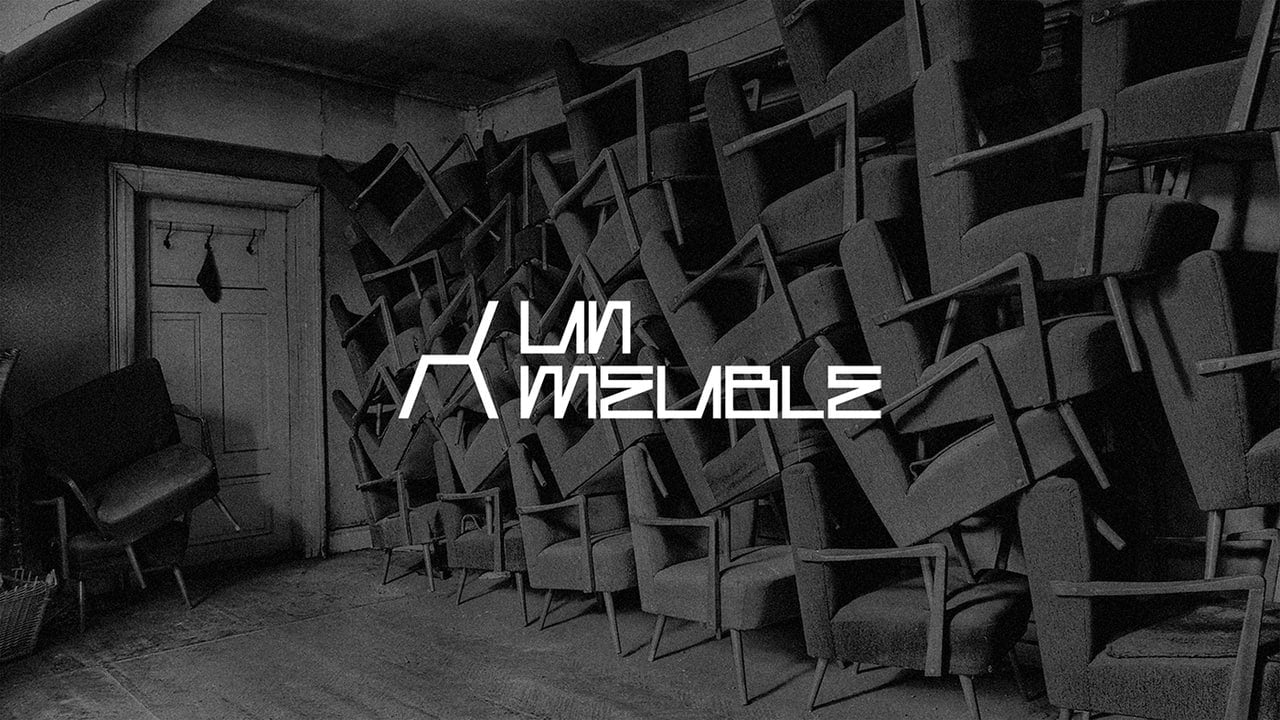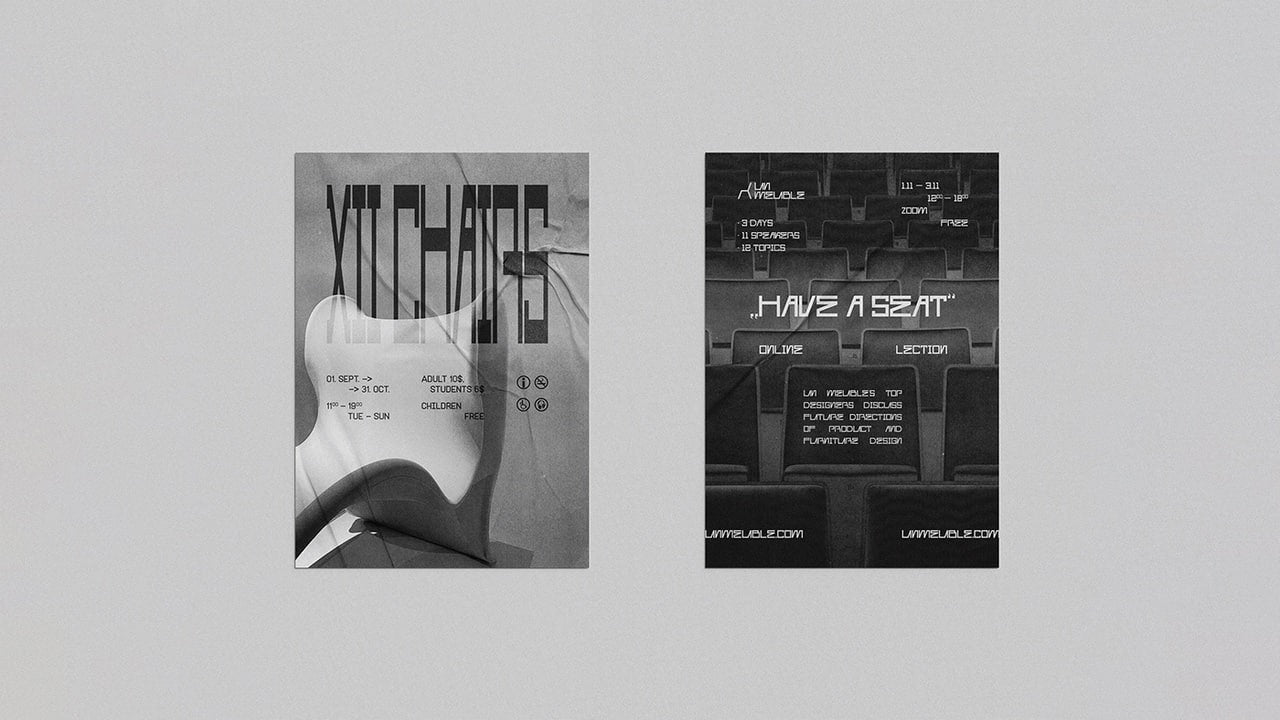
Un Meuble Display Font
Inspirée par le design épuré d'un logo créé pour un magasin de meubles conceptuel par Iryna Kovalenko, Un Meuble Display Font est une police de caractères innovante, minimaliste et géométrique qui transformera vos projets.
Un Meuble comprend les majuscules, les chiffres, la ponctuation et une gamme de symboles, offrant une grande polyvalence pour toutes vos créations.